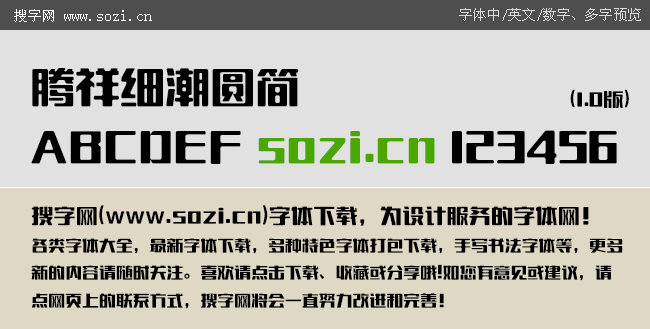
騰祥細潮圓簡
搜字網(wǎng)提供一款騰祥細潮圓簡中文藝術字體下載,騰祥細潮圓簡將細潮黑的棱角柔化形成被融化之感,融化了的筆畫圓潤富于親和力。字形結構扁方、端莊,橫豎筆畫粗細比例適度、豎筆粗壯有力,布白均勻、行文貫通。騰祥細潮圓簡筆畫簡潔圓潤細微處變換靈動,即實用又富有裝飾效果,且清晰易讀,適合標題和屏顯用字,可用于印刷出版、包裝設計、廣告設計、網(wǎng)頁設計、屏幕顯示等。